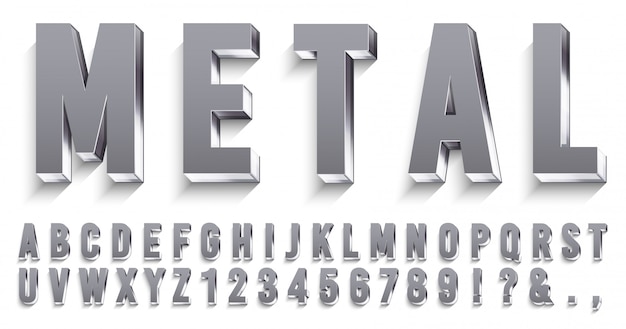
Шрифт меча содержит 5 глифов для нижнего регистра, 4 глифа для верхнего регистра и 4 альтернативы для каждого числа вместе с набором символов от A до Z. Он также поддерживает несколько языков.